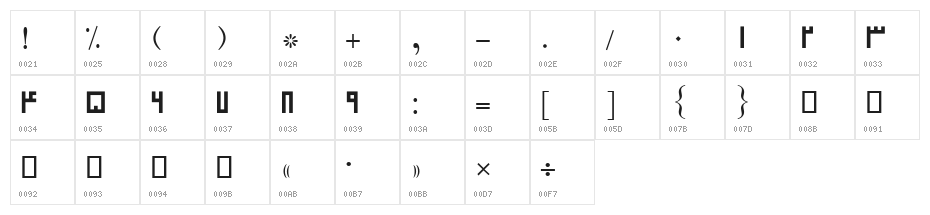
Kabah II Font
گالری فانت فارسی پژوهش آريانا - only compatible with Farsi and Arabic
| Autore | گالری فانت فارسی پژوهش آريانا - only compatible with Farsi and Arabic |